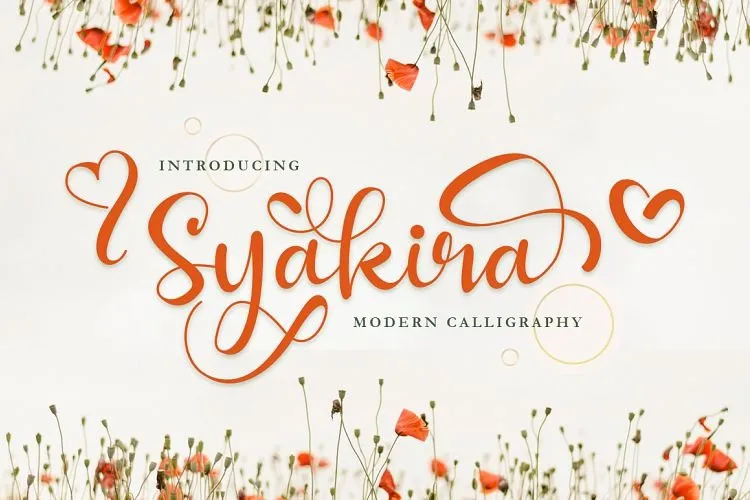
Syakira Calligraphy Font – Fonte Grátis
Syakira Calligraphy Font
A Syakira Calligraphy Font é uma fonte que traz alegria e romantismo para seus projetos digitais. Perfeita para o Dia dos Namorados, esta fonte é ideal para personalizar qualquer design do qual você esteja trabalhando. Desenvolvida pela EmbunStudio, a Syakira Calligraphy oferece uma alternativa estilizada de estilo chamado calligrafia. Seus traços delicados, suas linhas curvas suaves e seus detalhes decorativos tornam esta fonte perfeita para criar projetos únicos, como frames personalizados, convites de aniversário ou cartas de agradecimento. Faz com que cada projeto fique ainda mais elegante e cheio de vida. O Syakira Calligraphy é uma escolha ideal se você busca dar um toque único a qualquer trabalho gráfico.